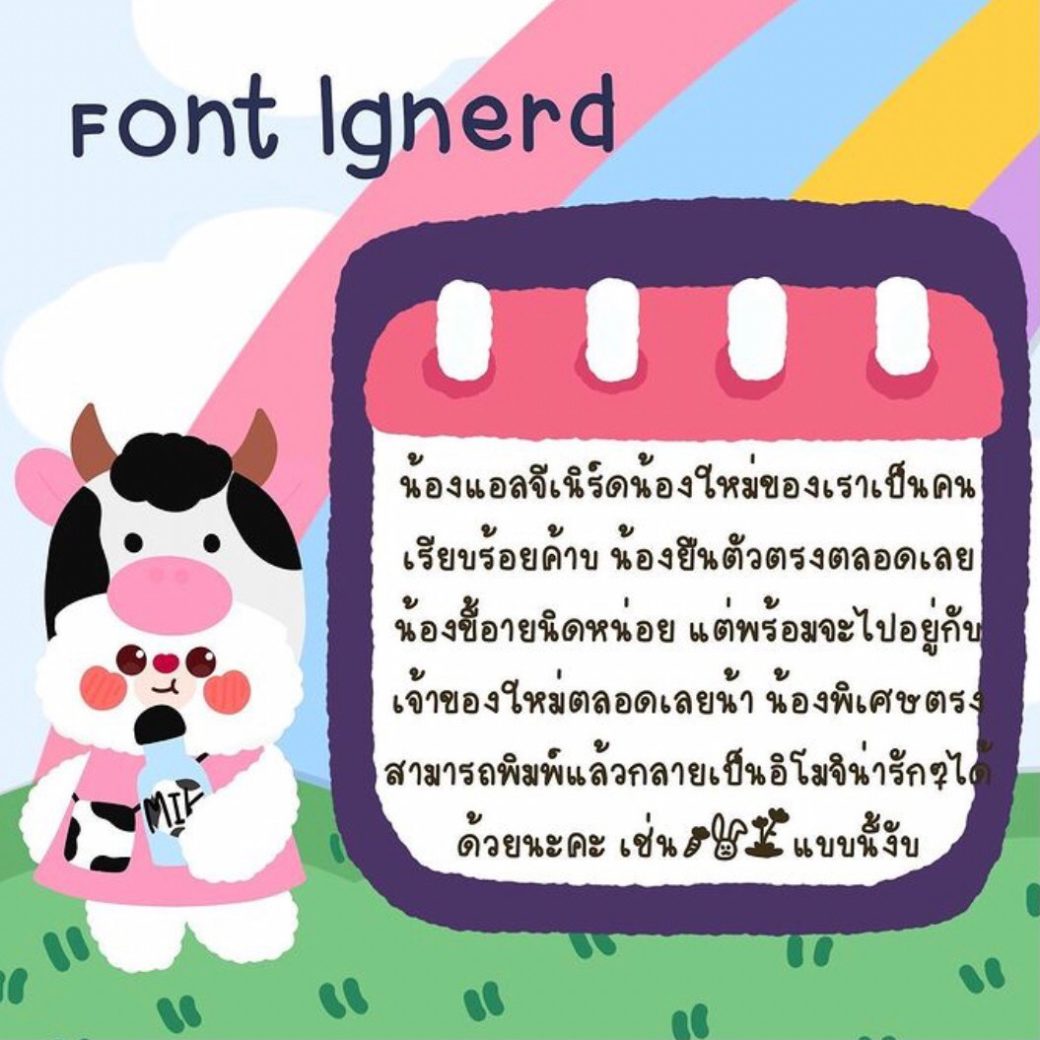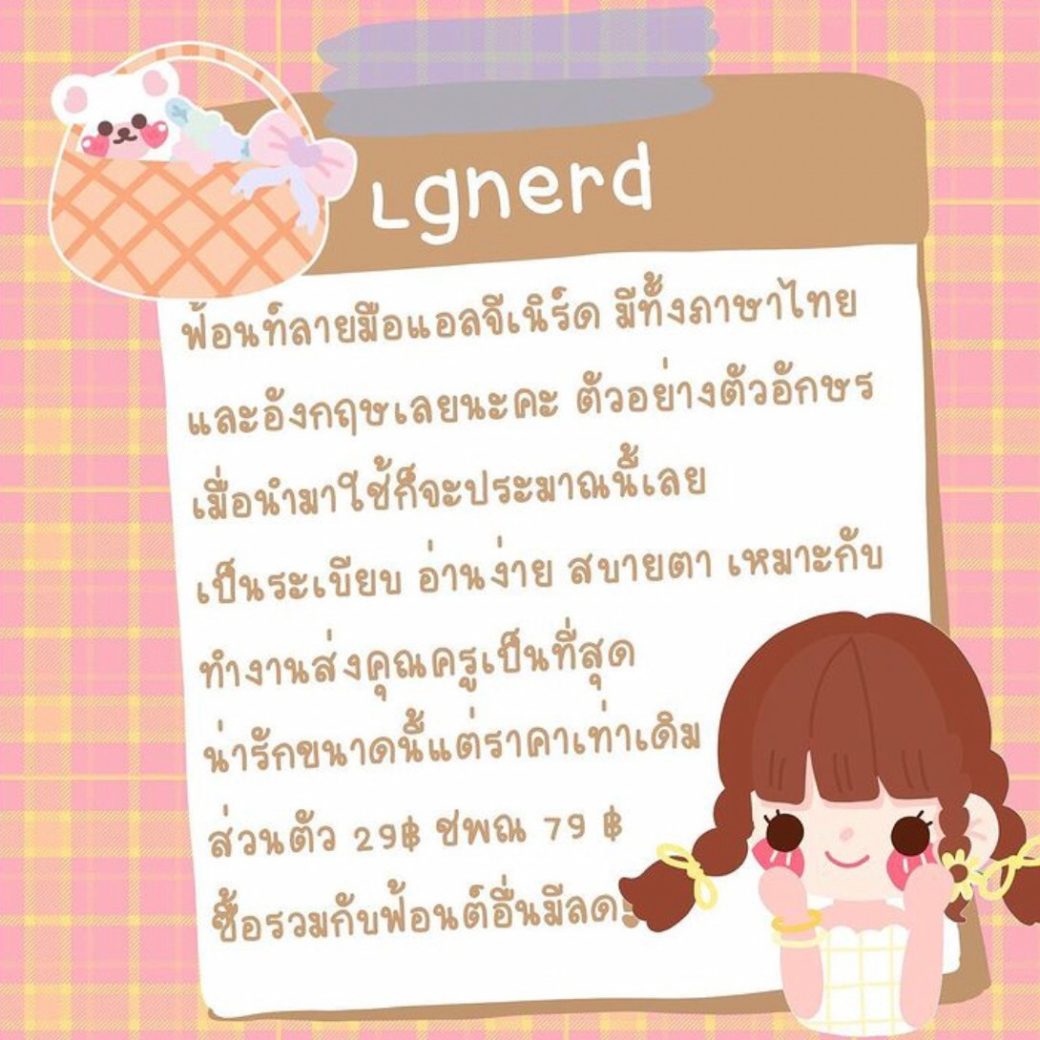
ฟ้อนท์ลายมือ lgnerd – Font
ฟ้อนท์ลายมือ lgnerd
มาในตีมเด็กเรียบร้อยงับ ยืนตัวตรงเรียบร้อยมั่กๆ
🥞🧋ฟ้อนท์แอลจีเนิร์ด จากร้านแอลจี
❗️อักษรพิเศษ/อิโมจิการ์ตูน; กดเครื่องหมายเลขไทย